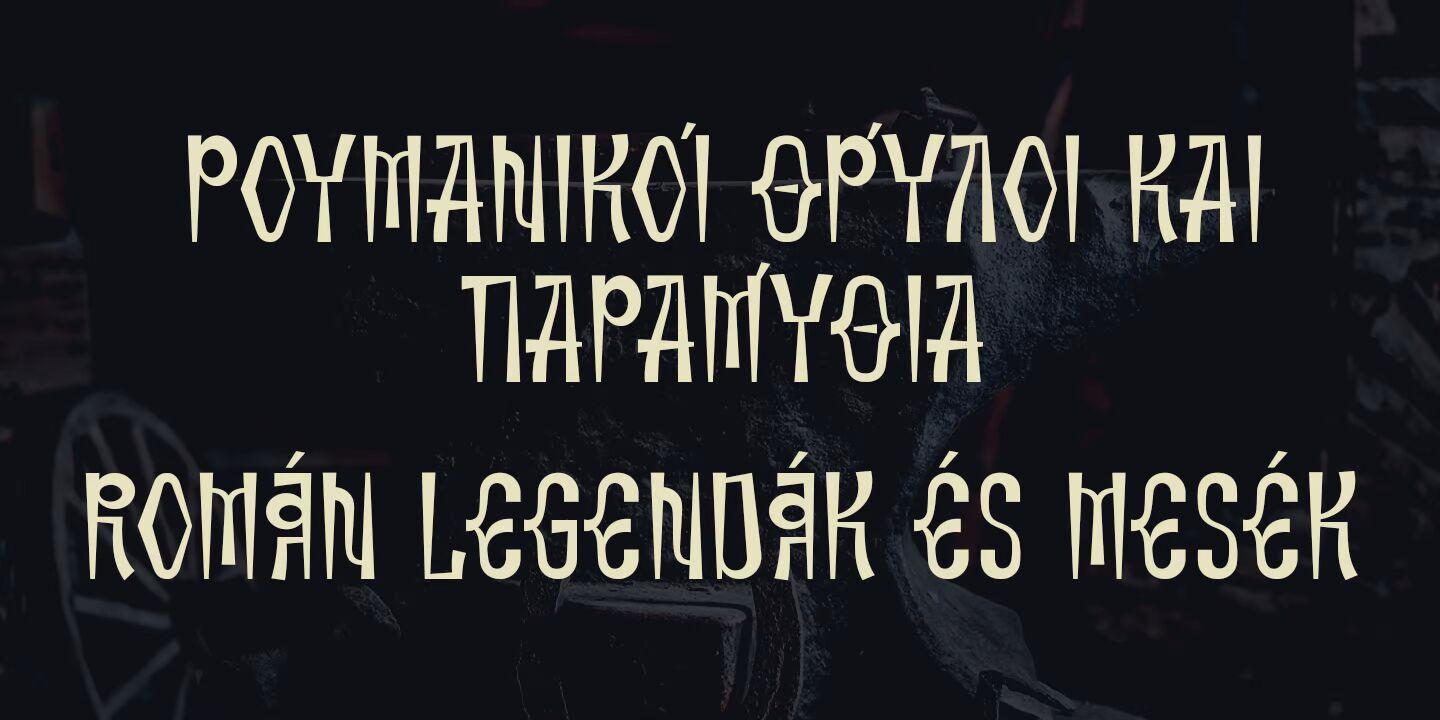
Greuceanu Font
Description de Greuceanu Font
Greuceanu est le nom d’un courageux personnage de conte de fées roumain dont la mission était de libérer le Soleil et la Lune qui ont été volés par des créatures ressemblant à des dragons que dans le folklore roumain on appelle « Zmei ». Cela m’a inspiré pour créer cette police d’affichage décorative en majuscules avec de solides influences de l’ancienne écriture cyrillique et une touche d’explorations de construction amusantes et géométriques. En outre, la prise en charge latine étendue inclut les alphabets cyrillique et grec, comme vous pouvez vous y attendre dans la plupart des versions de DePlictis Types. Cette police décorative convient parfaitement aux couvertures de livres et aux titres ; seule votre créativité limite sa convivialité.